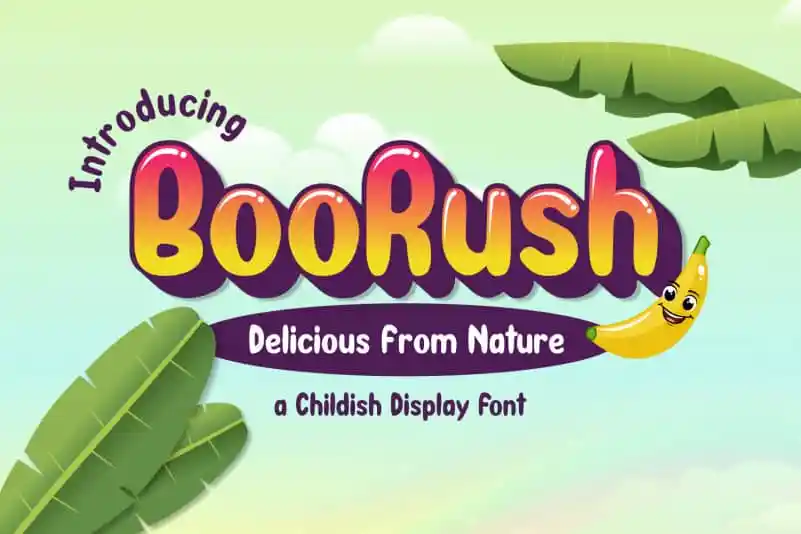
BooRush Display Font – Fonte Grátis
BooRush Display Font
A BooRush Display Font é uma opção divertida para aqueles que buscam um toque descontraído em seus projetos digitais. Inspirada em texturas infantis, esta fonte ganha vida com sua forma bold e firme, tornando-a perfeita para criar encorpados e alegres títulos. Seja você criando um site de crianças cheio de atividades ou simplesmente adicionando uma pitada de inocência a seus textos mais formais, BooRush atende suas necessidades com fidelidade ao estilo original. Suave quando necessário, mas decididamente forte e divertido, BooRush é perfeito para destacar seu design, especialmente em elementos visuais que precisam chamar atenção. Experimente ela em seus projetos e adicione um toque de diversão semelhante àqueles desenhos animados favoritos da infância às suas criações digitais.